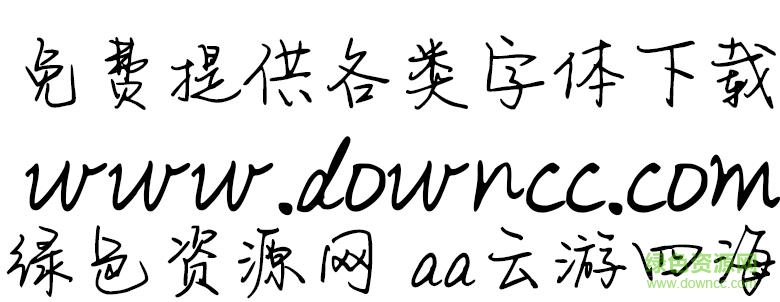
aa云游四海體字體是一款精美的擁有自主字體風(fēng)格,能夠讓你不斷感受到暢快的字體使用享受,這款讓人有種遺世獨(dú)立的感覺,字形十分瀟灑流暢,看起來很舒服,大家可以在綠色資源網(wǎng)下載使用哦!
aa云游四海字體在使用的時候真的驚艷到了我,很好看,很獨(dú)特,是一款十分瀟灑的字體,每一個字體都很隨意,就像一個鋼筆字大師所寫的字體!
字形瀟灑,自由隨性,年少時的夢幻想在遠(yuǎn)方,想落星湖的花海萬里,遙遙難及,像陽光落在赤道與北極,不爭朝夕